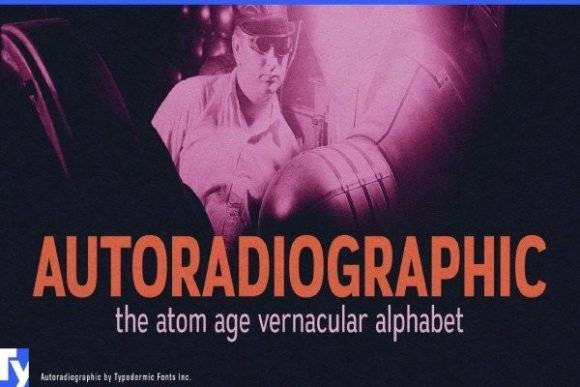
Fonte autorradiográfica para títulos, pôsteres e projetos de identidade visual.
Faça uma viagem no tempo com a fonte Autoradiographic , uma tipografia sem serifa disponível em 5 pesos. Inspirada nos sinais de aviso pintados à mão de meados do século XX, ela combina uma aparência limpa e técnica com uma personalidade sutil.
Principais características:
- Fonte sem serifa
- 5 pesos
- Inspiração de meados do século XX
- Limpo e técnico, com personalidade.
Perfeita para projetos que exigem uma combinação de charme vintage e clareza moderna, a fonte Autoradiographic é marcante e inesquecível.